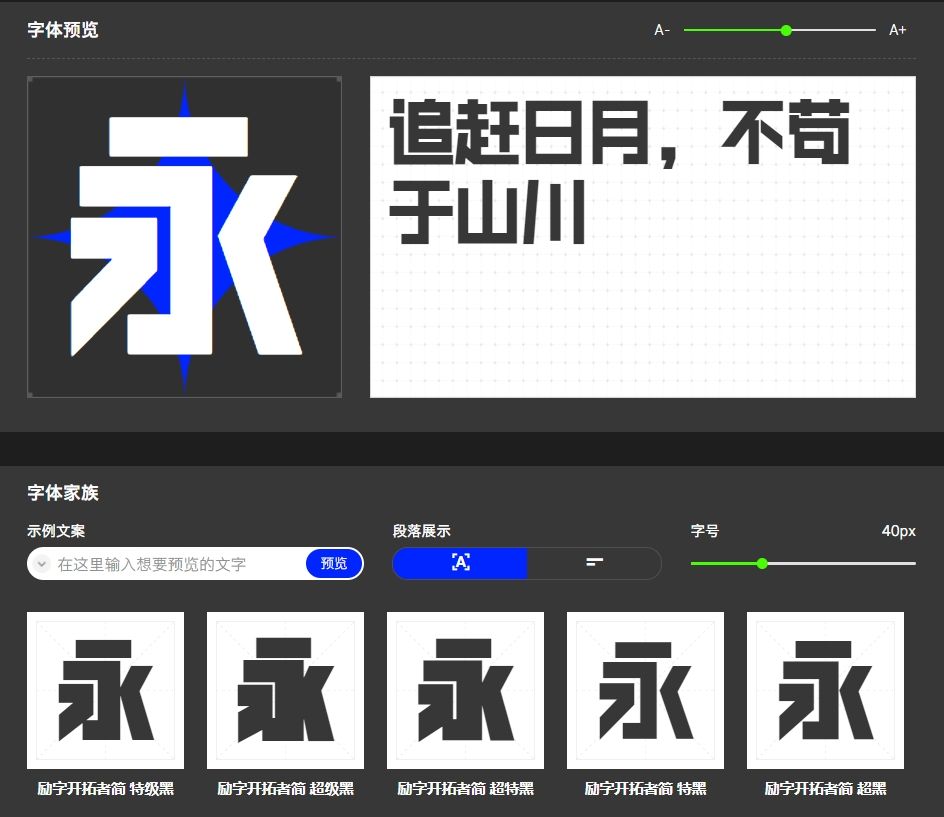
小红书创意字体:让你的文案更具魅力!
在小红书这个充满创意与个性的平台上,字体选择对于文案的吸引力有着至关重要的作用。一个好的字体不仅能让文案更具可读性,还能彰显出作者的独特品味和风格。下面,就为大家推荐几款适合小红书文案的字体,让你的文字更具魅力!
励字开拓者简 特黑:这款字体线条简洁流畅,既具有现代感又不失稳重,非常适合用于分享时尚穿搭、美妆教程等生活方式的文案。
励字乐悠悠简 常规,这款字体甜美可爱,带有明显的少女感,适合用于分享美妆、时尚、恋爱等话题的文案。
在小红书上发布文案时,选择合适的字体至关重要。通过本文推荐的简约时尚、文艺复古、清新可爱等字体,结合文案主题、目标受众、可读性和个性化等因素,你将能够打造出更具魅力的文案,吸引更多读者的关注和喜爱。不妨试试这些字体,让你的小红书文案更加出彩吧!